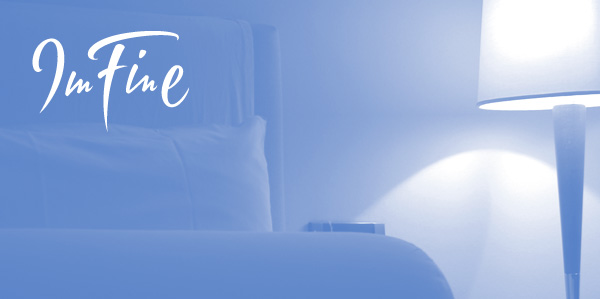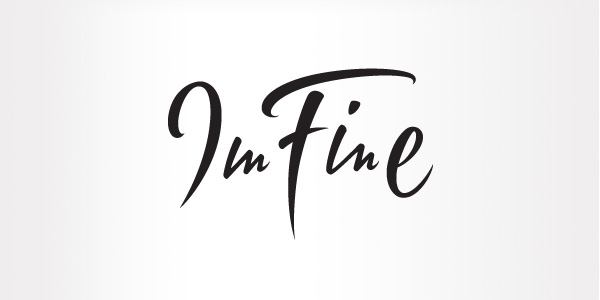
ImFine
Каллиграфический логотип для марки постельного белья ImFine. Бельё, дающее расслабление, отдых и, как следствие, хорошее настроение. Живое динамичное письмо остроконечной кистью. Графически зарифмованные «m» и «in» слегка стилизованы под стежки.